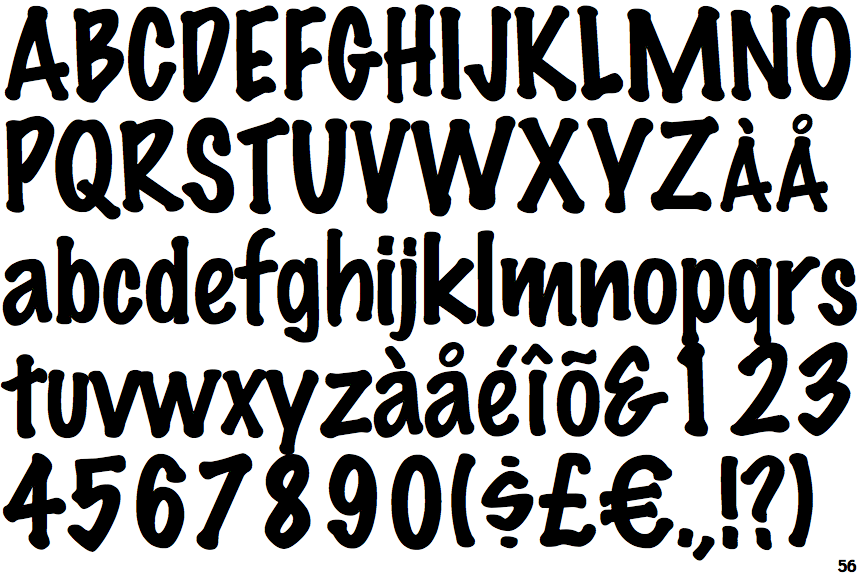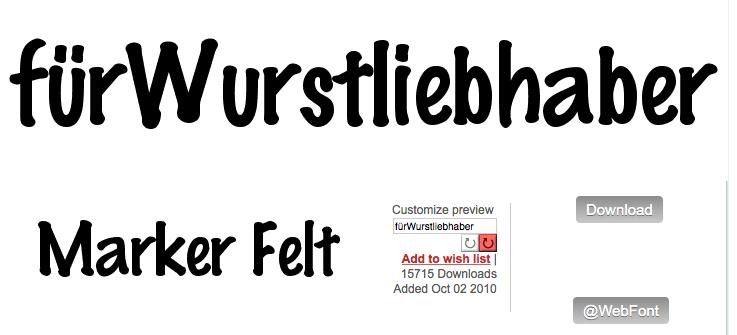
Hausschrift einer Metzgerei
ich lege 1Spruch gegen diesen Vorschlag ein:
Das kleine a passt nicht. Marker Felt entspricht da der Marker Acct von Gerber Signs, eine Schrift für Folien ... ? Aber die ist es IMHO nicht (so ganz). Man werfe aber einen Blick auf Apples Marker Felt Thin: